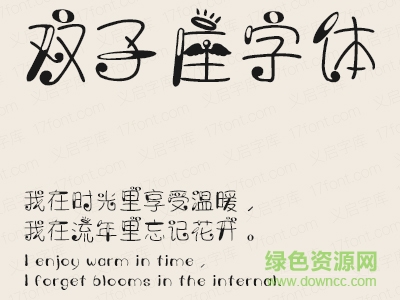
義啟雙子座字體是一款義啟星座字體,雙子座的朋友們不要錯(cuò)過(guò)了自己的專(zhuān)屬字體喲,筆畫(huà)可愛(ài),富有樂(lè)趣園,如同卡通形象活起來(lái)一般。歡迎大家來(lái)綠色資源網(wǎng)下載義啟字體!
義啟雙子座字體,話(huà)癆的雙子座為黃道十二宮之第三宮,在餐桌上肯定是用來(lái)聊天的,唾沫橫飛的那個(gè)肯定就是雙子座了,和雙子座寶寶吃飯記得帶傘哦。